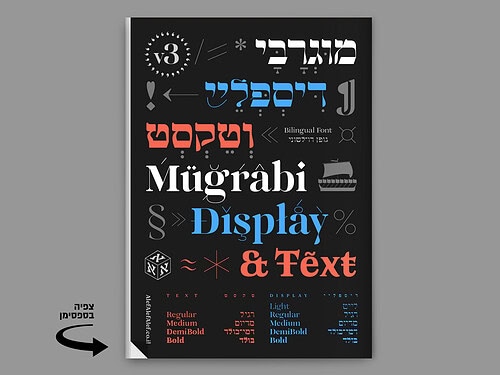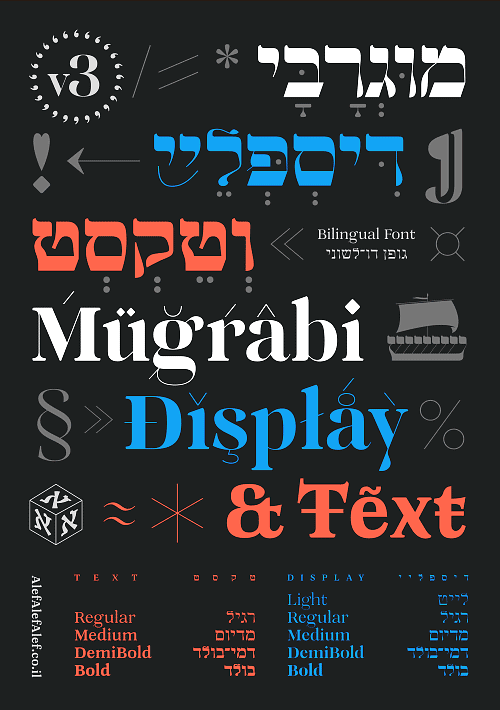
על אודות פונט מוגרבי טקסט
הרחבה דו־לשונית לאחד הפונטים האהובים בספריית אאא. המשפחה נחלקת לשתי גרסאות משלימות:Mugrabi Text לטקסט־רץ ו־Mugrabi Display לכותרות.
מקורה של מוגרבי באות עברית קלאסית מתוך קטלוג בצלאל, שם הופיעה בשם ״ספרדי״. חידוש האות נשען על כרזות ישנות של סרטים שהוקרנו בקולנוע מוגרבי בתל־אביב. אף שמעט ידוע על זהות מעצבה, ניכר בה קשר לאות היוגנדסטיל שרווחה בדפוס היהודי באירופה.
הגרסה החדשה כוללת גם מערכת לטינית מקורית, ושומרת על המתח הייחודי בין הקווים האנכיים והאופקיים, תוך התאמה לצרכים הטיפוגרפיים של ימינו.
OpenType Features
- ליגטורות סודיות אשכרה ← אשכרה
- עץ אל וגם ששש יי ff ft gg
- חלופות סגנוניות ע ← ע
- ל ← ל
- @ ← @
- 4 1 ← 4 1
- & & & ₪ ₪ ₪
- אותיות רחבות ﬡבﬢﬣחﬤﬥﬦﬧﬨ
- סוואשים בראשית ← בראשית
- מספרים טבלאיים 12,345,678.90 ← 12,345,678.90
- סמלים ⁕ ♥ ❣ ⁆ ❞ ¶ ⛵ ✱ ॐ